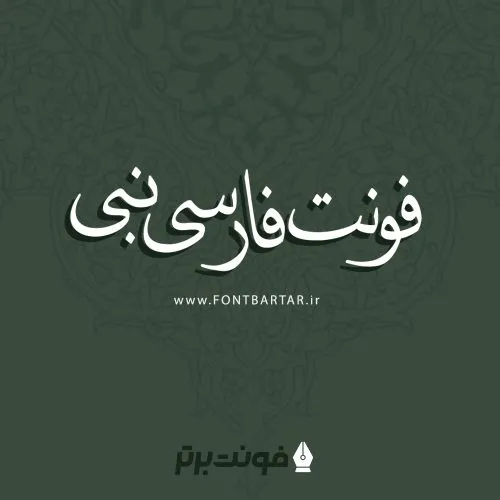
فونت نبی
فونت فارسی نبی
فونت نبی ( Nabi ) از سری فونت های خوشنویسی می باشد، از این فونت فارسی می توانید در متن هایی که نیاز به خوش نویسی دارن استفاده کنید، برای طراحی این فونت زیبا حدود 1 سال زحمت کشیده شده است، این قلم زیبا دارای اعراب و کشیدگی ها را که با Shift+J این کشیدگی ها قبل از هر حرف قابل اعمال است.
فونت نبی مورد استفاده برای:
• طراحان وب سایت و گرافیست های خلاق می توانند از این فونت زیبا فونت در طراحی پروژه های تبلیغاتی و تجاری خود کمک بگیرند.